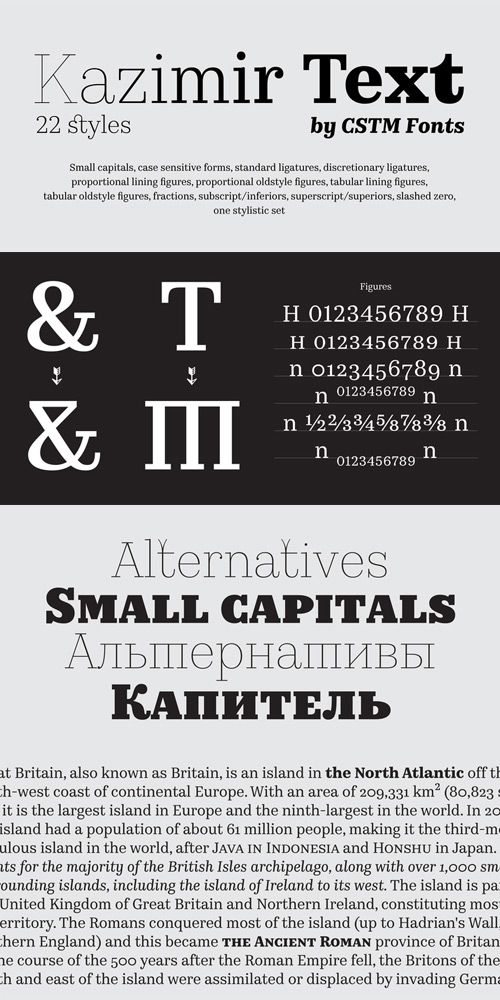
Kazimir Text - стильный шрифт
Kazimir Text представляет собой современные засечеки с довольно простой графической идеей. Это текстовая версия дисплея Kazimir Text, шрифт имеет немного более широкие пропорции, немного более низкую контрастность и гораздо шире кодовую страницу с расширенной поддержкой языка по сравнению с Kazimir.
Шрифт поддерживает русский язык
Первый шрифт Kazimir тоже хорош. В паре они вообще шикарно работают.
Один из лучших кириллических шрифтов с засечками.